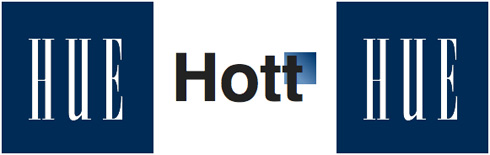
GAP Inc. ist der größte US-amerikanische Bekleidungseinzelhändler, gegründet 1969 in San Francisco. Der Name leitet sich ab von den Differenzen zwischen Jugendlichen und Eltern (“the generation gap”), im Deutschen als Generationenkonflikt bekannt. Zum GAP-Markenimperium gehören noch Banana Republic, Old Navy, Piperlime und Athleta. Das Engagement des Konzerns in Deutschland endete 2004 mit dem Verkauf aller Filialen an den größten europäischen Konkurrenten Hennes & Mauritz (H&M).
Letzte Woche unternahm GAP den Versuch, klammheimlich ein neues Logo zu lancieren. Dieses stieß nicht nur rein äußerlich auf Kritik (»GAP hat sein ikonenhaftes Logo gegen etwas ausgetauscht, was wie ein 17 Dollar teures Machwerk aus der Microsoft-Word-Clip-Art-Galerie aussieht.« Brandchannel), auch die Methode wurde von Fachleuten als unnötige »Markenpanik-Aktion« bezeichnet. Dabei hat sich der Konzern offensichtlich keine Gedanken darüber gemacht, die Auswirkungen dieses Schrittes zu durchdenken. Die Marke ist groß geworden mit den Attributen neu und hip, wieso sollten die Kunden diesem Schritt nicht folgen? Die Einführung des neuen Logos geriet zum Rohrkrepierer. Vergangene Nacht brach die Marke den Versuch eines Rebrandings wieder ab.
GAP hat drei Dinge nicht beachtet:
1. Die wichtigste Käufergruppe, die US-Kunden, haben genug von Change und ›Yes We Can‹. Die Bloggerin Laura Black formuliert es so: “We’ve had enough change thank you. We’d like to feel we can count on a few things in our lives to remain consistent.”
2. Die Marke gehört den Kunden. Der information architect (iA) Oliver Reichenstein formulierte es heute Morgen auf Twitter so: »The Brand is what *they* say it is.« Dieses Zitat steht in ähnlicher Form in vielen Marketing-Lehrbüchern. Reichenstein hat es einer 4 Jahre alten, überaus lehrreichen Präsentation mit dem doppelsinnigen Titel “The Brand Gap” entnommen, die sich dem Selbstbild und dem Fremdbild von Marken widmet.
3. Die Vernetzung der Kunden. GAP hat die neue Macht der Kunden übersehen und unterschätzt. Wie ein Orkan stürmte die Kritik zum neuen Logo via Twitter und Facebook auf das Modelabel ein. Im Nu entstanden Webseiten, auf denen Besucher »Neues-GAP-Logo«-Imitationen generieren konnte (www.craplogo.me und www.makeyourowngaplogo.com), auf Twitter griff ein schlecht gelauntes Fake @gaplogo den Hype auf um Kritikern frech zu kontern, FastCompany führte ein exklusives Interview mit dem neuen Logo und natürlich meldeten sich auch die Design-Experten zu Wort (z. B. Brand New) … wobei zum ersten Mal die Kunden die Macht hatten. Unterdessen schrieben sich die GAP-Markenmanager auf Facebook die Finger wund.
Gestern Nacht hieß es dann aus der GAP-Zentrale: GAP hört auf die Kunden und behält das klassisch blaue Quadrat-Logo. In der offiziellen Stellungnahme schreibt GAP-USA-Präsident Marka Hansen: »Wir haben gelernt, wie viel Energie mit unserer Marke verbunden ist. Alle Argumente führten zurück zum blauen Quadrat, und so haben wir uns dazu entschlossen, das neue GAP-Logo auf gap.com nicht mehr einzusetzen. … Wir haben viel aus der Sache gelernt. Wir sind den falschen Weg gegangen. Uns wurde auch klar, dass wir die Möglichkeit mit der Online-Community zu sprechen versäumt haben. Es war das falsche Projekt für den geeigneten Zeitpunkt eines Crowd-Sourcing.«
Aufpassen, Herr Hansen. Ich zitieren lieber noch mal in Originalsprache: “This wasn’t the right project at the right time for crowd sourcing.” Sollte es irgendwann mal ein richtiges GAP-Projekt für ein Crowd-Sourcing geben, dann bitte keines, das in die Hände erfahrener Markenexperten und Designer gehört … so Dinge wie Ihre Produkte und Ihr Logo. Nach der ersten Welle der Kritik haben sie auf Facebook einen Logo-Crowd-Sourcing-Wettbewerb vorgeschlagen. Tanz auf dem Vulkan.
Leider kennen wie die Umstände der Entstehung des neuen Logos nicht, für das angeblich eine professionelle Agentur (Laird & Partners) verantwortlich ist. Oder wurde sie vielleicht gar nicht gefragt … oder gehört?
Wenn man sich ansieht, wie vieles heute unter Kritik gerät und wie wenig Verantwortliche auf diese Kritik reagieren, muss man eigentlich schon den Hut ziehen vor der Bereitschaft einen Fehler einzugestehen. Gefällt mir! (Mal davon abgesehen, ob dabei wirtschaftliche Interessen eine Rolle gespielt haben. So etwas erfordert trotzdem immer etwas Mut und Demut. Bitte mehr davon!)
Hmmm, GAP ist so reich; ich kann mir nicht helfen, meint Ihr nicht es kann auch eine riesengroße PR-Aktion gewesen sein? Also alles (ich meine wirklich alles) erstunken und erlogen? Wäre doch eine Möglichkeit…?
Wäre es nicht mutiger gewesen, man wäre trotz aller Kritik beim neuen Logo geblieben? Wenn man tatsächlich Mut gezeigt und 100% hinter dem Entwurf gestanden hätte, wäre dies nicht bemerkenswerter? So knickt man vor der (laut klappernden) Masse ein und suhlt sich im Konsens des breiten Geschmacks.
Gut, nun ist das neue Logo wirklich ziemlicher Mist … aber ist es nicht das falsche Signal, wenn man nur darauf hört, was vermeintlich alle wollen? Das gipfelt in einem absoluten Stillstand, wenn keinerlei Änderungen mehr akzeptiert werden und alles Neue weggebuht wird.
Wenn das eine PR-Aktion war, dann wird das Laird & Partners teuer zu stehen kommen.